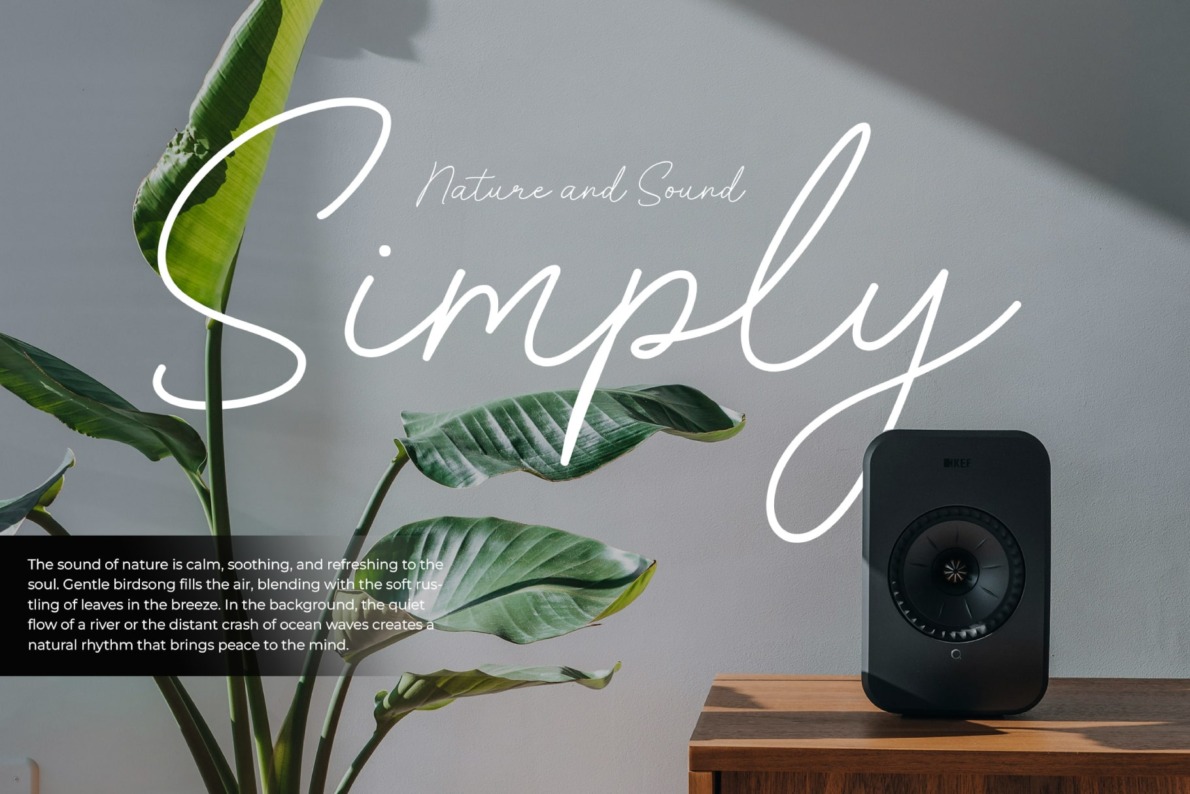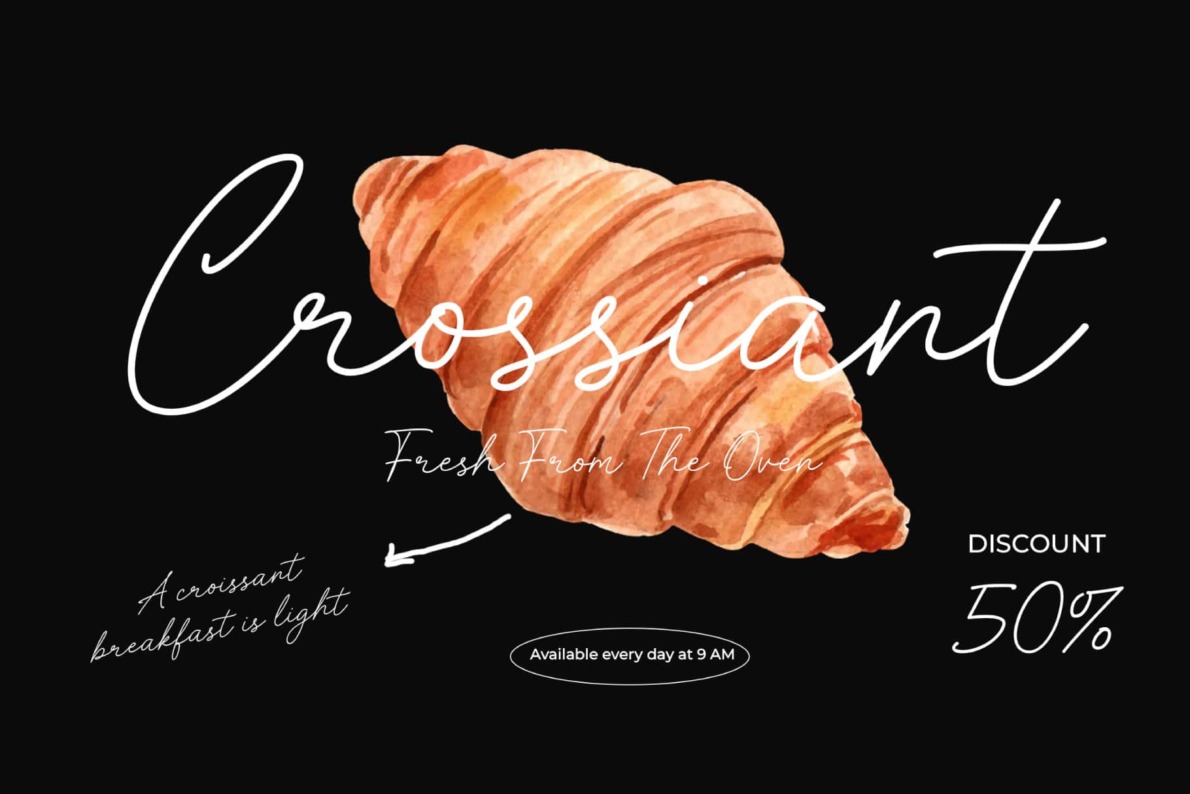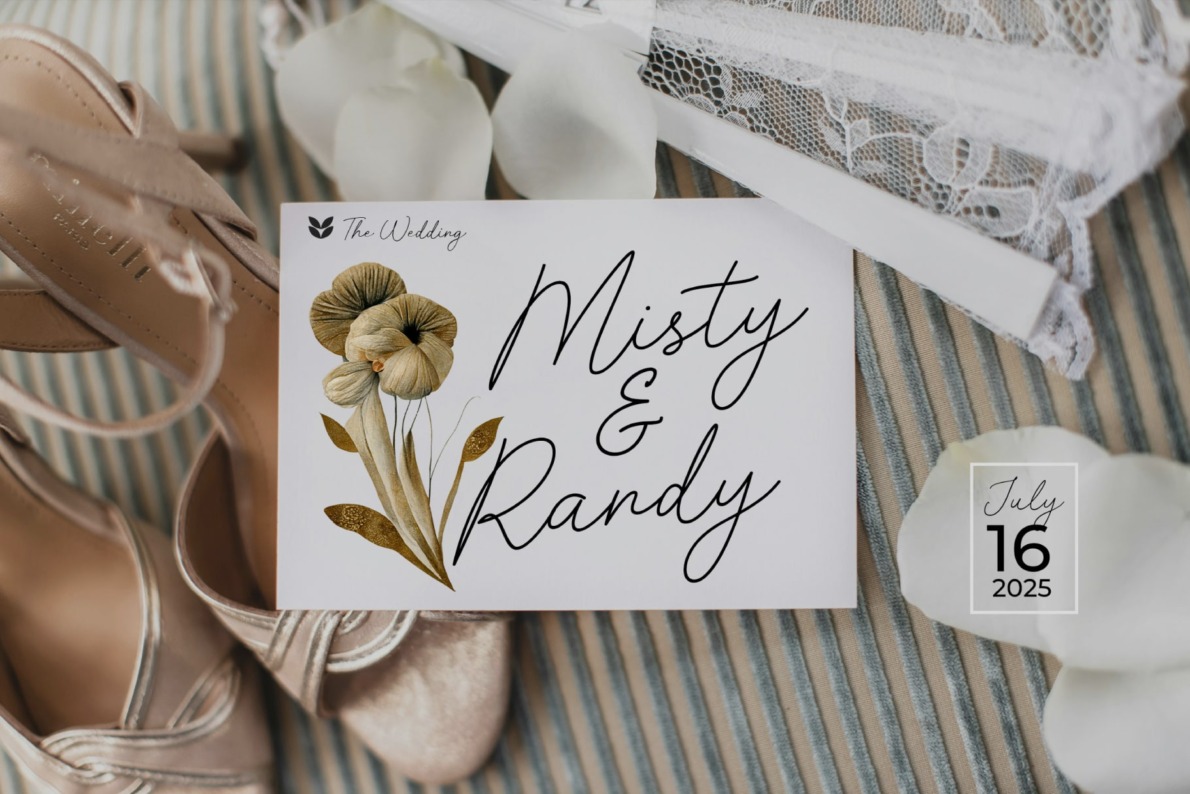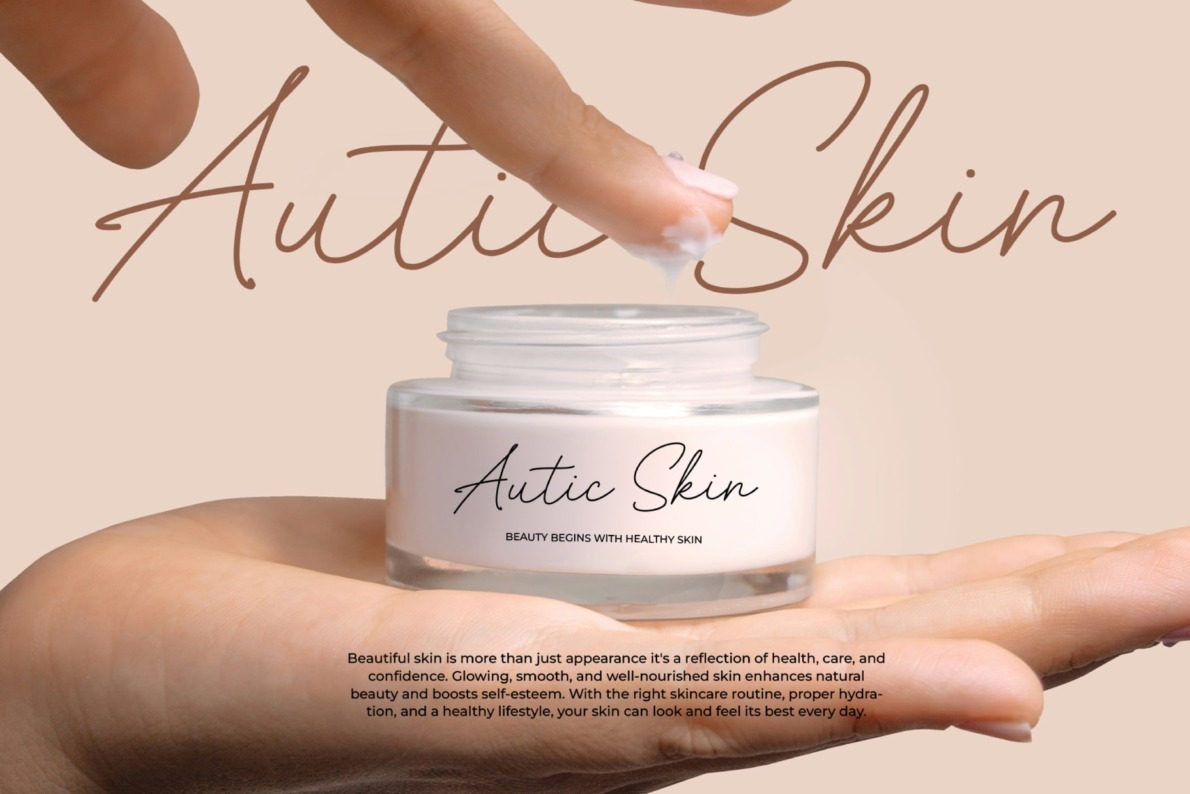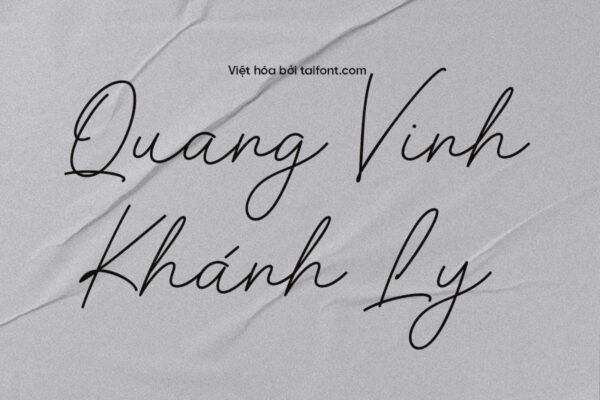
Giới thiệu Font TF Misty Grey Việt hóa
TF Misty Grey là một font chữ ký viết tay mang đậm phong cách sang trọng và tinh tế, rất phù hợp cho các thiết kế thiệp cưới hoặc những ấn phẩm yêu cầu sự trang nhã và quý phái. Các nét chữ uốn lượn mềm mại nhưng vững chắc giúp font mang lại cảm giác lãng mạn, thanh lịch mà vẫn nổi bật.
Phiên bản Việt hóa đã hỗ trợ đầy đủ dấu tiếng Việt, giúp font dễ dàng áp dụng vào các thiết kế thiệp cưới, tiêu đề, hoặc các sản phẩm quảng cáo mỹ phẩm cao cấp. Font này còn có thể được sử dụng trong các thiết kế tiêu đề sang trọng, bao bì mỹ phẩm, hay các ấn phẩm có tính chất tinh tế.
Nếu bạn đang tìm một font Việt hóa miễn phí mang phong cách chữ ký đẹp, thanh lịch và dễ ứng dụng cho thiệp cưới hay các ấn phẩm liên quan đến mỹ phẩm, TF Misty Grey là lựa chọn lý tưởng.
Điểm nổi bật của TF Misty Grey Việt hóa
Việt hóa đầy đủ dấu tiếng Việt.
Kiểu chữ ký mềm mại, thanh lịch và trang trọng.
Lý tưởng cho thiết kế thiệp cưới, tiêu đề, mỹ phẩm và các sản phẩm sang trọng.
Tạo cảm giác tinh tế, lãng mạn và quý phái.
Font TF Misty Grey Việt Hóa – Font Chữ Ký Sang Trọng Cho Thiết Kế Thiệp Cưới